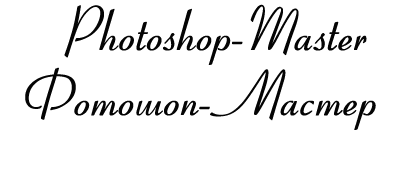
Этим шрифтом было написано "The End" во многих сериях мультфильма Tom and Jarry, наконец-таки я тебя нашёл! =)
Классный шрифт)
Забавно!
Просто и со вкусом!